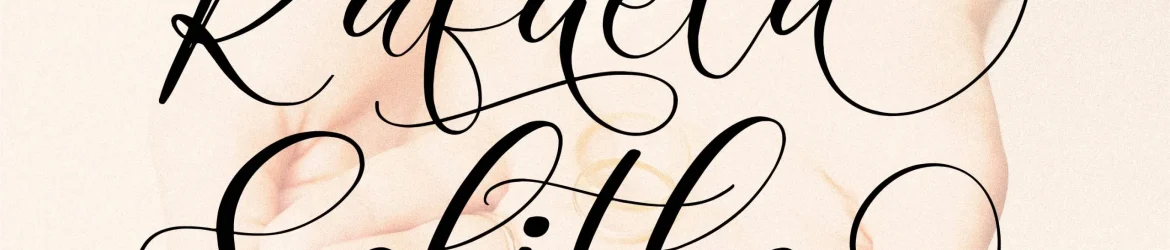
A font ‘Rafaela Salitha’ é perfeitamente adaptada para projetos que exigem uma escrituração delicada e romântica. Idealmente, ela se encaixa em diversas categorias de design como logos, embalagens de produtos, capas de livros, cartões de convite, adesivos, materiais promocionais e até mesmo para criações digitais como ícones e marcas. Suavizar suas mensagens com o ‘Rafaela Salitha’ pode transformar seus projetos em verdadeiras obras de arte. Este é um belo complemento para qualquer designer que deseja dar aos seus trabalhos uma dose a mais de elegância e charme, tornando-os ainda mais memoráveis.